Font chữ lịch sử việt hoá mang ngôn ngữ thị giác của những trang sách cũ, bia đá và ấn phẩm học thuật tạo ra cảm giác trang trọng, có chiều sâu thời gian mà font hiện đại không thể thay thế. Bài viết, In Viva sẽ tổng hợp các font chữ lịch sử miễn phí, đáng tải sử dụng cho thiết kế tài liệu, sự kiện văn hóa và bao bì cao cấp.
Tải font chữ lịch sử Việt hóa miễn phí giúp bạn dễ dàng ứng dụng vào thiết kế mang phong cách cổ điển, sang trọng mà vẫn đảm bảo hiển thị đầy đủ tiếng Việt. Với nhiều định dạng phổ biến, bạn có thể sử dụng linh hoạt cho PowerPoint, Photoshop hay in ấn mà không lo lỗi font.
Đặc điểm của nhóm font chữ lịch sử
Font lịch sử là nhóm font lấy cảm hứng từ các hệ thống chữ viết và kỹ thuật in ấn của các thời kỳ lịch sử cụ thể. Khác với font cổ điển tổng quát, mỗi font lịch sử mang dấu ấn của một thời kỳ hoặc nền văn hóa riêng.
- Roman cổ đại (Cinzel, Trajan): Lấy cảm hứng từ chữ khắc trên bia đá La Mã thế kỷ 1–2. Nét tương phản cao, không Italic, tất cả chữ hoa. Tạo cảm giác quyền lực và vĩnh cửu.
- Serif thế kỷ 18 (Playfair Display, Bodoni): Thời kỳ hoàng kim của in ấn, nét tương phản cực cao giữa nét đứng dày và nét ngang mảnh. Sang trọng và tinh tế.
- Typewriter và báo cổ (IM Fell English): Phục dựng font từ bộ sưu tập IM Fell của Đại học Oxford mang dấu ấn của báo in thủ công thế kỷ 17 với các nét chữ không hoàn hảo có chủ đích.
- Blackletter Gothic: Chữ Gothic trung cổ châu Âu, nét góc cạnh, dày và phức tạp. Phổ biến trong đề tên báo cổ, bia mộ và trang trí nhà thờ.
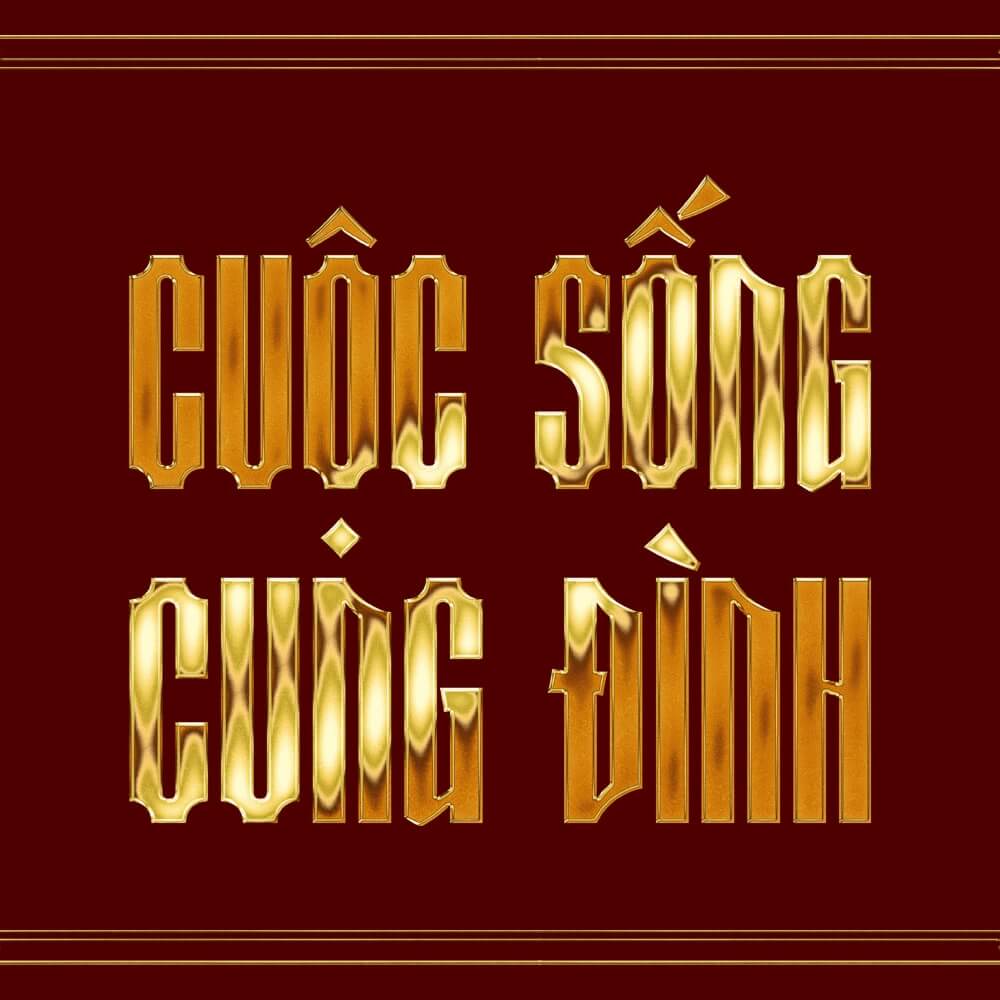
Ứng dụng của font lịch sử việt hoá trong thiết kế
Font lịch sử thường được ứng dụng trong các thiết kế cần cảm giác cổ điển, sang trọng và mang yếu tố di sản như bao bì cao cấp, sách hoặc ấn phẩm văn hóa.
- Tài liệu lịch sử, sách và ấn phẩm học thuật: IM Fell English và Cinzel tạo ra cảm giác tư liệu xác thực, phù hợp với xuất bản phẩm về lịch sử, văn hóa và học thuật.
- Bao bì rượu vang, rượu mạnh và sản phẩm cao cấp lâu năm: font Roman cổ đại và Playfair Display tạo ra nhãn sản phẩm gợi cảm giác thương hiệu lâu đời, bề thế và đáng tin cậy.
- Backdrop và ấn phẩm sự kiện văn hóa, kỷ niệm lịch sử: Cinzel Decorative và Cinzel ở cỡ lớn trên backdrop kỷ niệm ngày lịch sử tạo ra tông thị giác trang trọng và phù hợp ngữ cảnh.
- Logo thương hiệu muốn gợi cảm giác di sản và lâu đời: font Roman hoặc Blackletter dùng trong wordmark tạo cảm giác thương hiệu có lịch sử sâu dày, chiến lược được nhiều thương hiệu bia, rượu và thực phẩm truyền thống áp dụng.
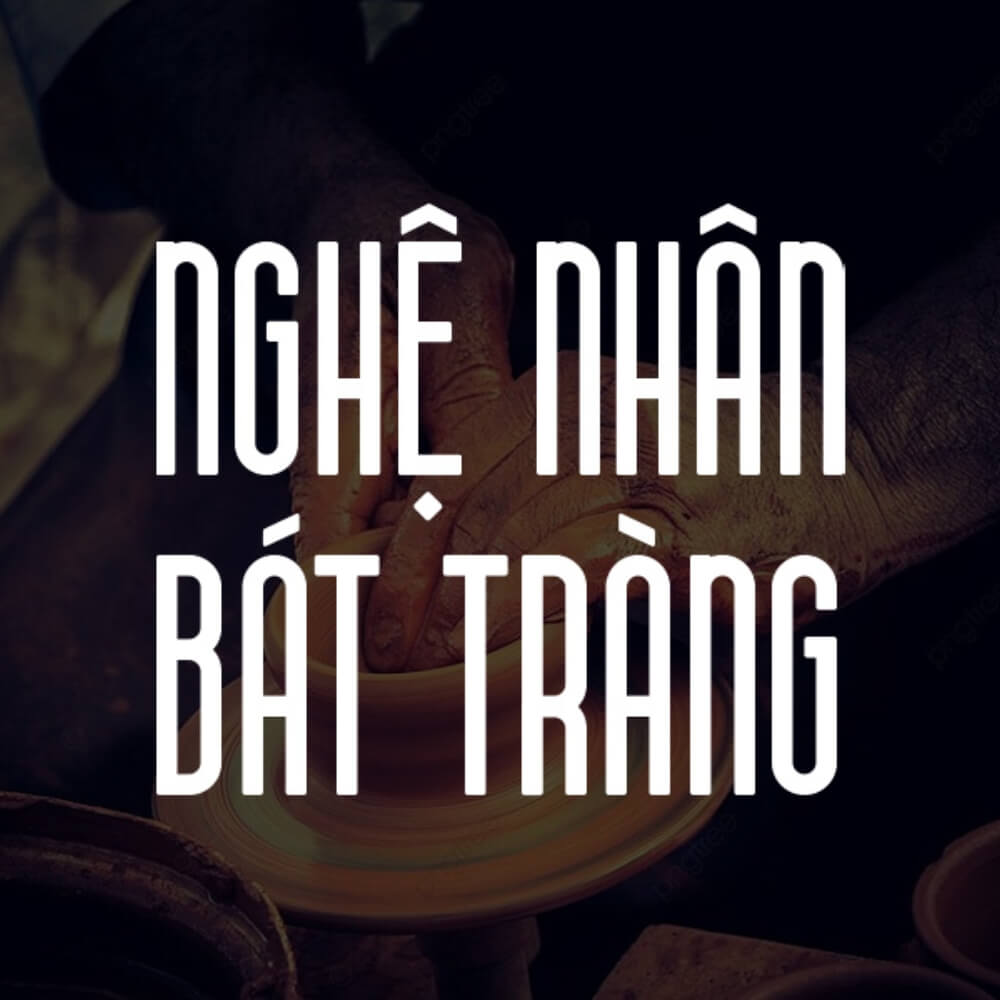
Lỗi thường gặp khi dùng font lịch sử
Font lịch sử mang lại cảm giác cổ điển, sang trọng và chiều sâu cho thiết kế. Tuy nhiên, để đạt hiệu quả tốt, cần sử dụng đúng ngữ cảnh và tránh các lỗi cơ bản khi áp dụng.
- Dùng Blackletter cho văn bản tiếng Việt dài. Blackletter Gothic không được thiết kế cho tiếng Việt — dấu tiếng Việt trên nền chữ Gothic phức tạp gần như không đọc được. Chỉ dùng Blackletter cho văn bản Latin hoặc tên thương hiệu ngắn, không dùng cho tiêu đề tiếng Việt đầy đủ.
- Phối font lịch sử với font hiện đại không cùng tông. Cinzel + Be Vietnam Pro tạo ra tương phản tốt giữa tiêu đề cổ điển và nội dung hiện đại. Nhưng Cinzel + font sans-serif geometric như Futura tạo ra sự xung đột thẩm mỹ vì hai font đến từ hai triết lý thiết kế đối lập.
- Dùng font lịch sử cho thương hiệu trẻ, năng động hoặc công nghệ. Font Roman và Blackletter gắn liền với sự truyền thống và nghiêm túc. Dùng cho startup công nghệ hoặc thương hiệu hướng đến gen Z tạo ra sự không nhất quán về định vị thương hiệu.
- Không kiểm tra hỗ trợ tiếng Việt trước khi dùng. Không phải font lịch sử nào trên Google Fonts cũng hỗ trợ đầy đủ ký tự tiếng Việt. Gõ thử văn bản cần dùng ngay sau khi cài để phát hiện ký tự bị thiếu trước khi đưa vào thiết kế chính thức.
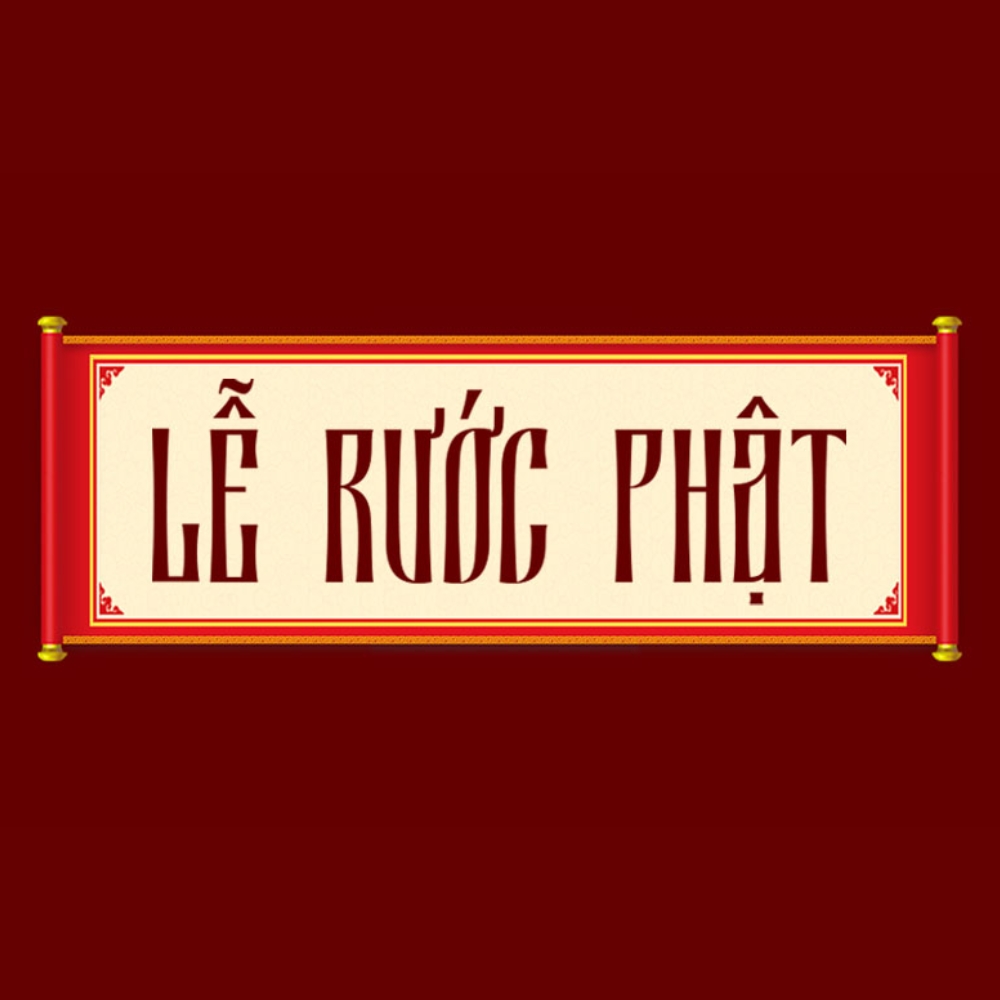
Font chữ lịch sử việt hóa in đẹp nhất trên chất liệu nào?
Giấy mỹ thuật không tráng phủ hoặc giấy có vân nhẹ. Chất liệu này tạo cảm giác ấn phẩm lâu đời và thủ công, kết hợp với font lịch sử cho ra sản phẩm có chiều sâu thẩm mỹ tốt hơn in trên giấy couche bóng.